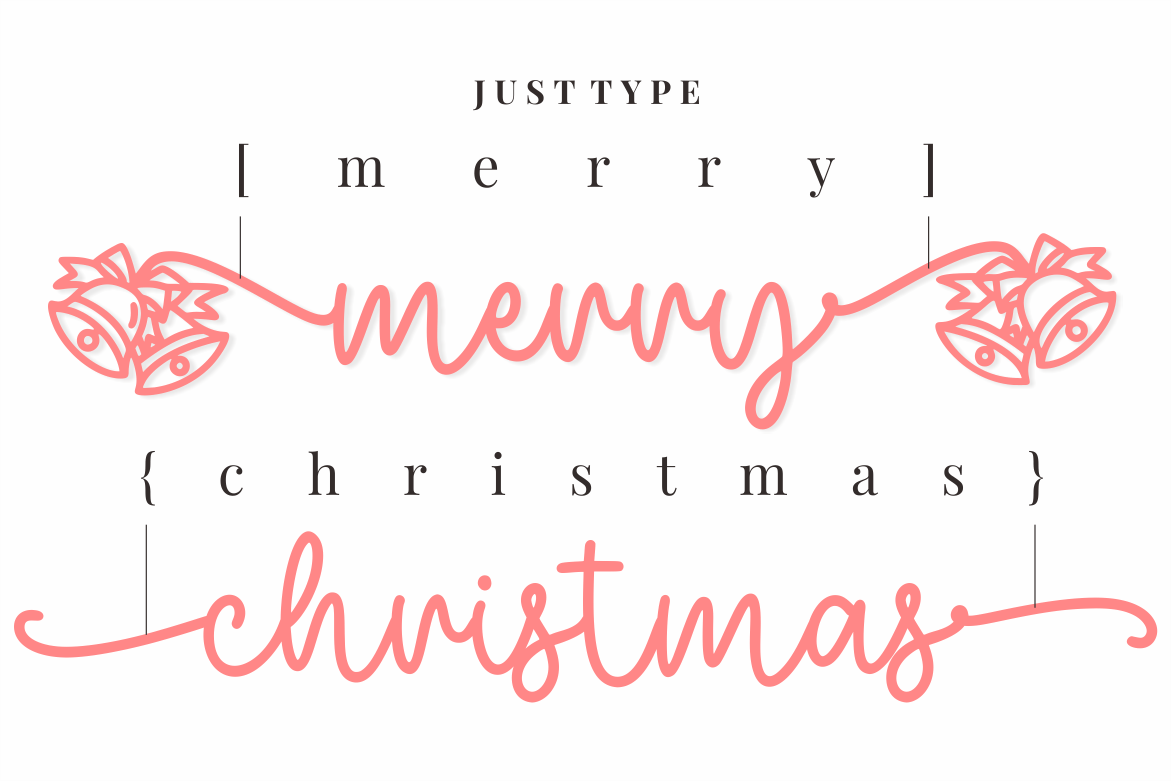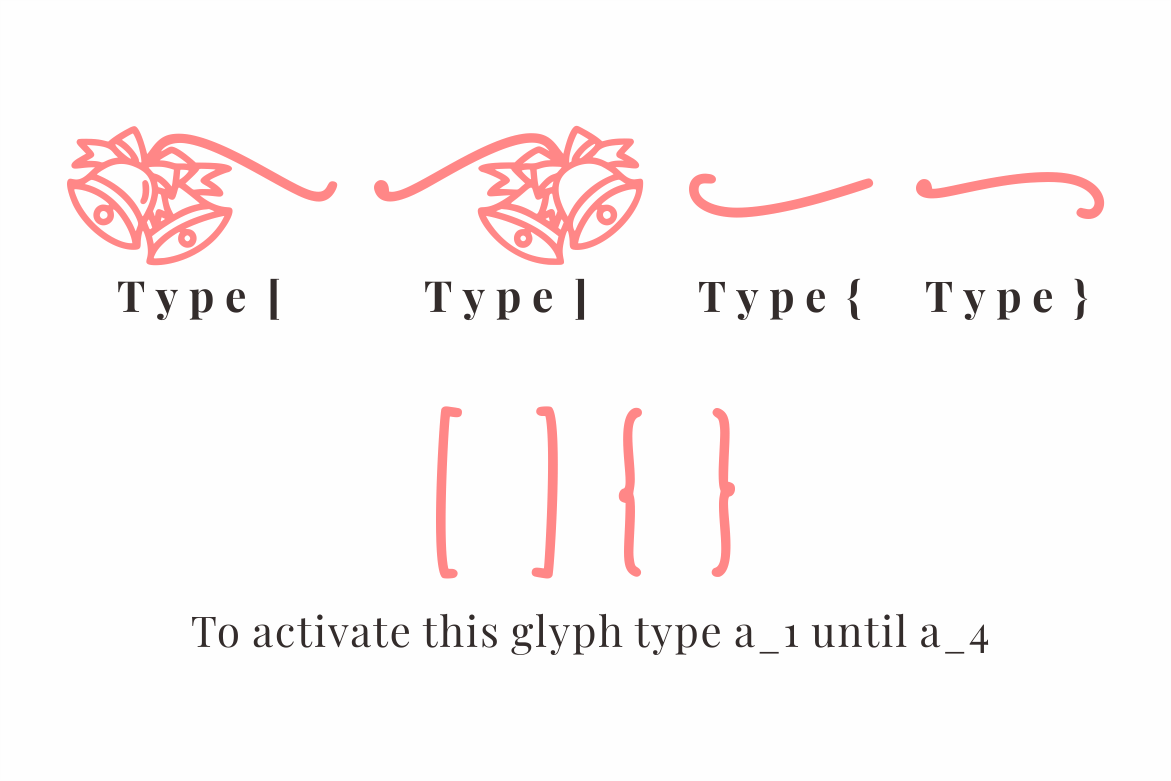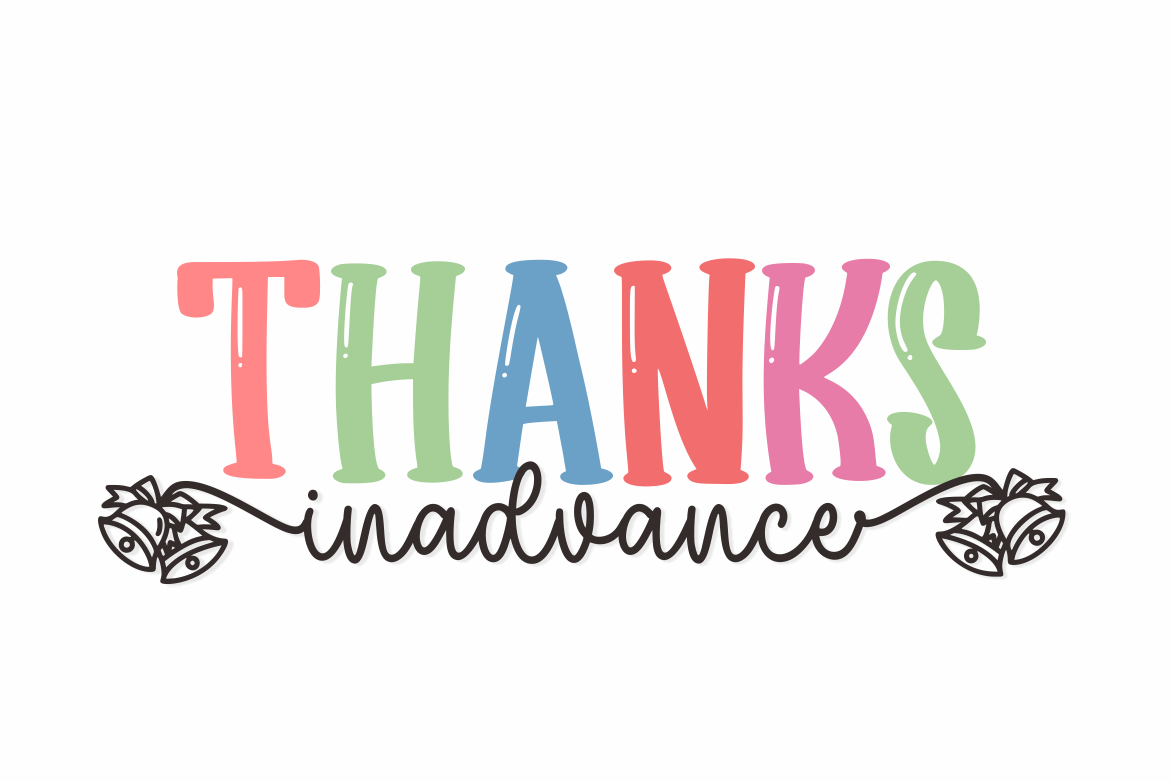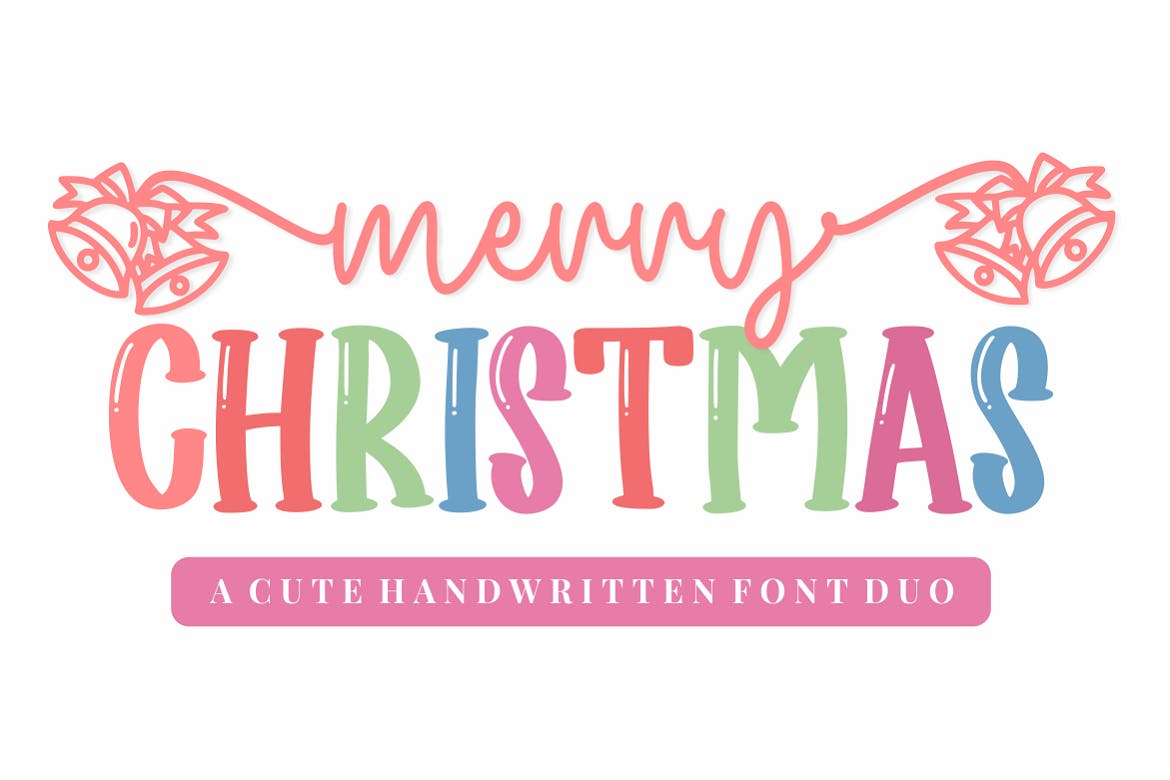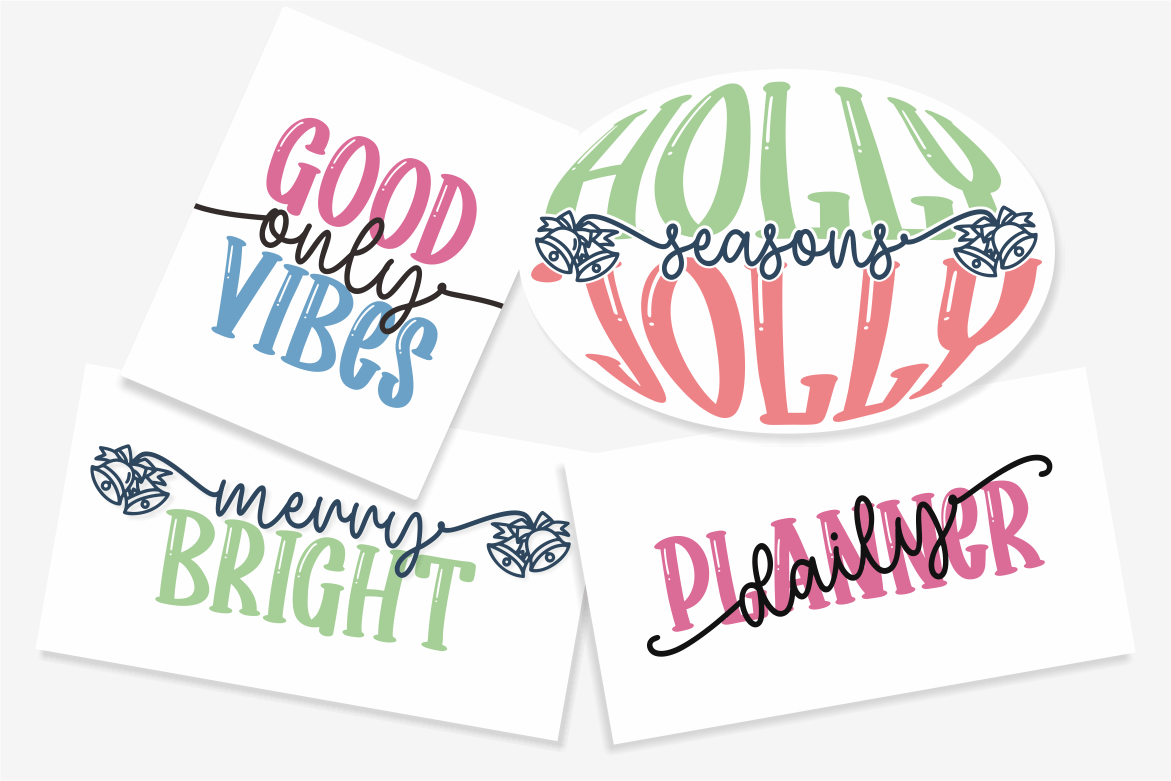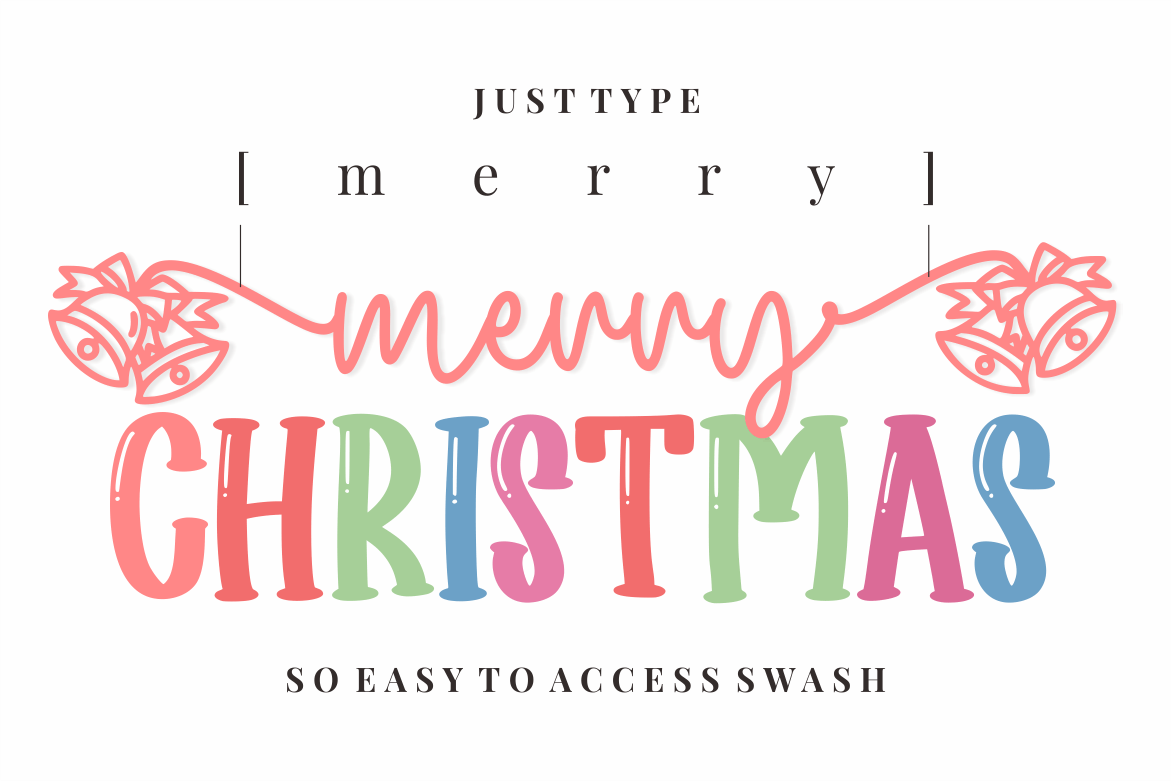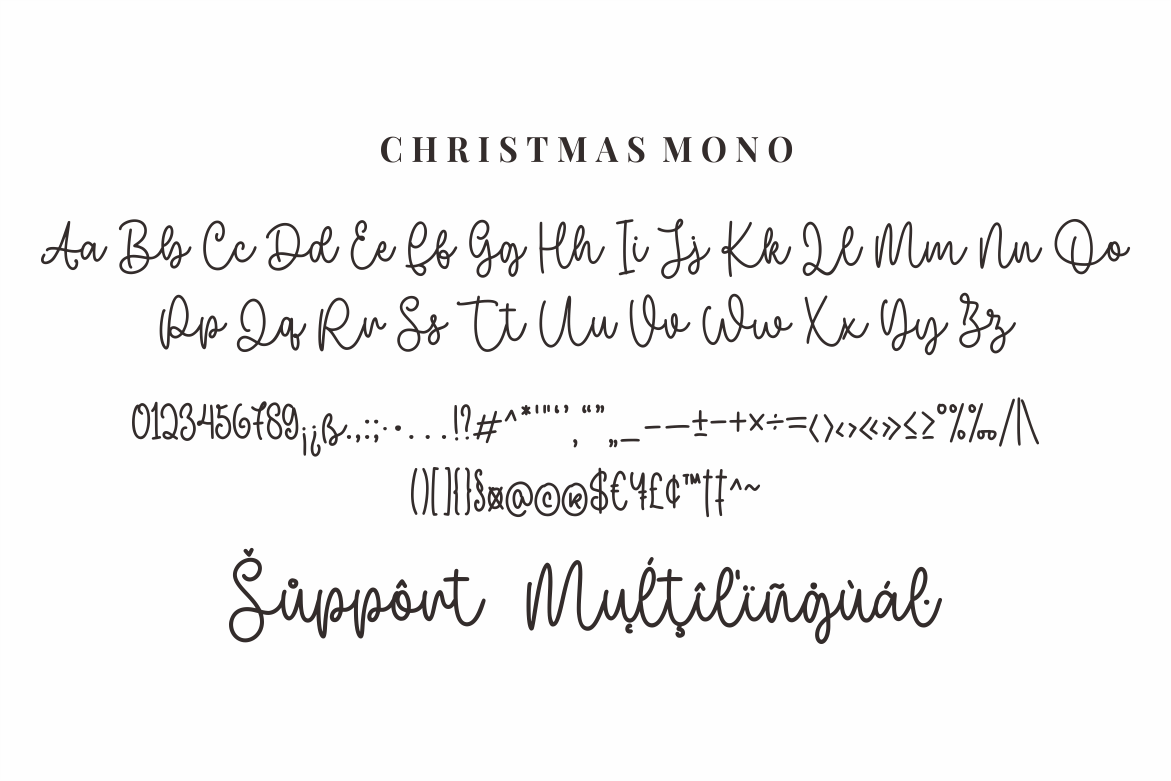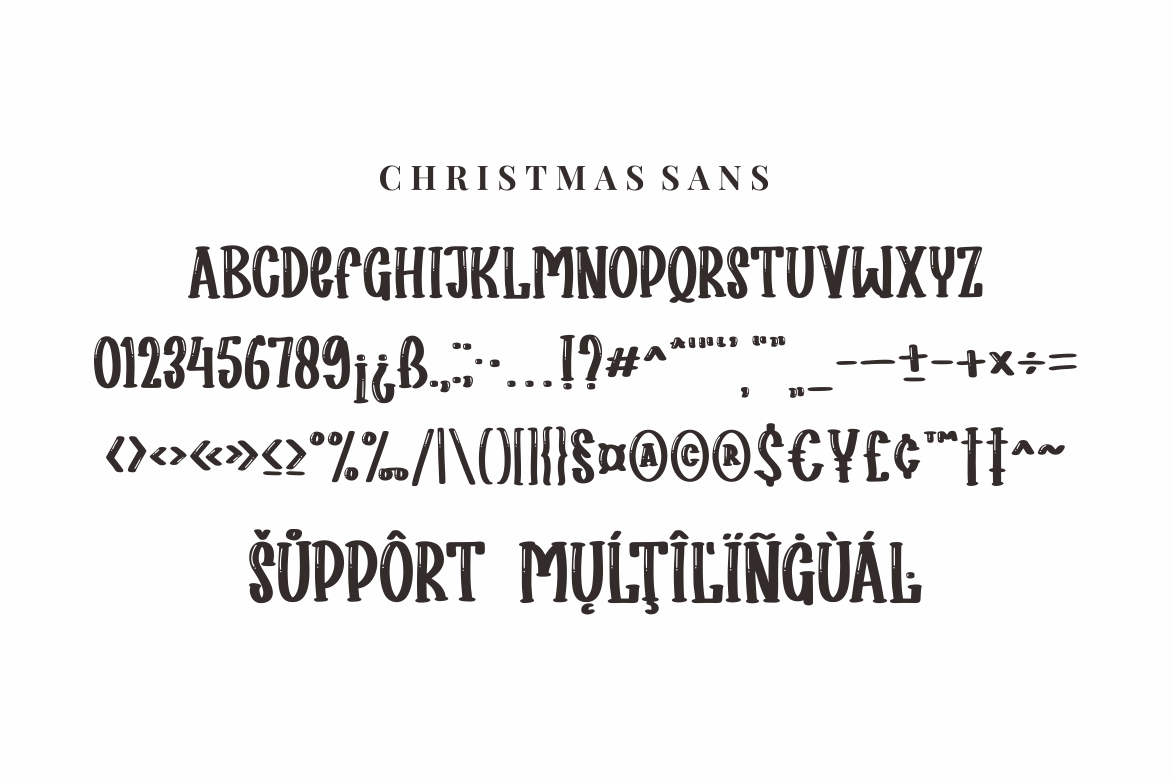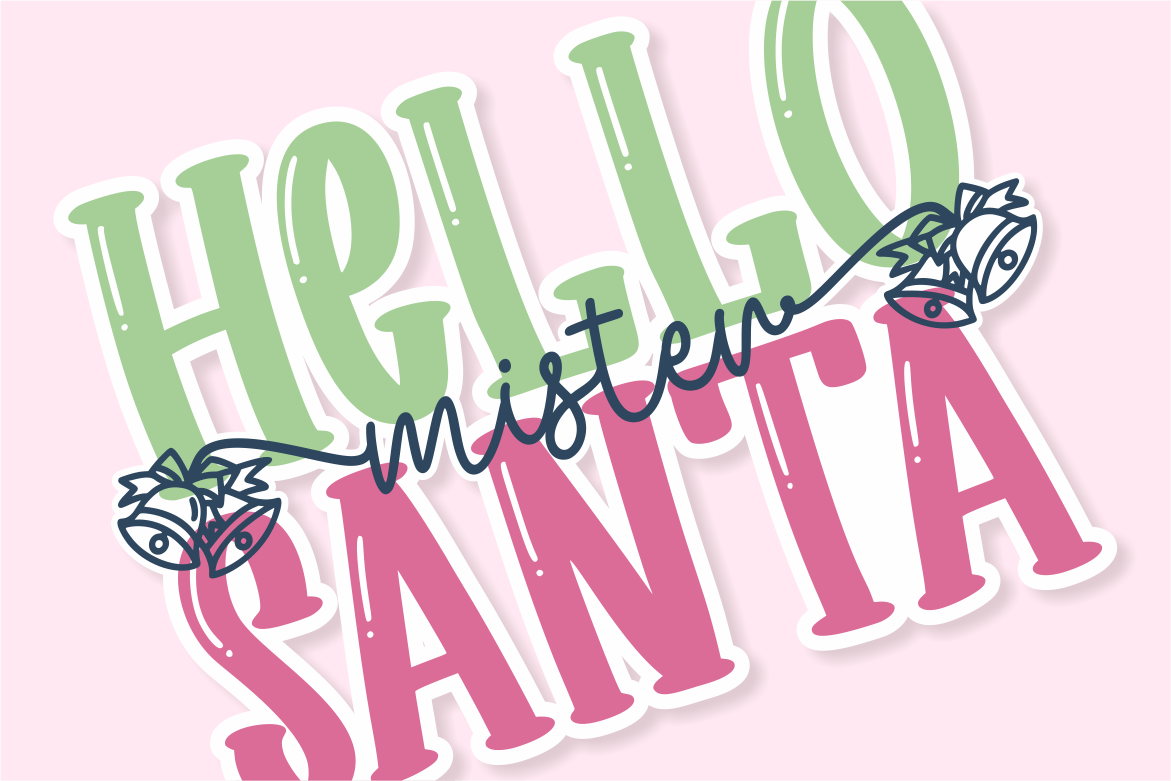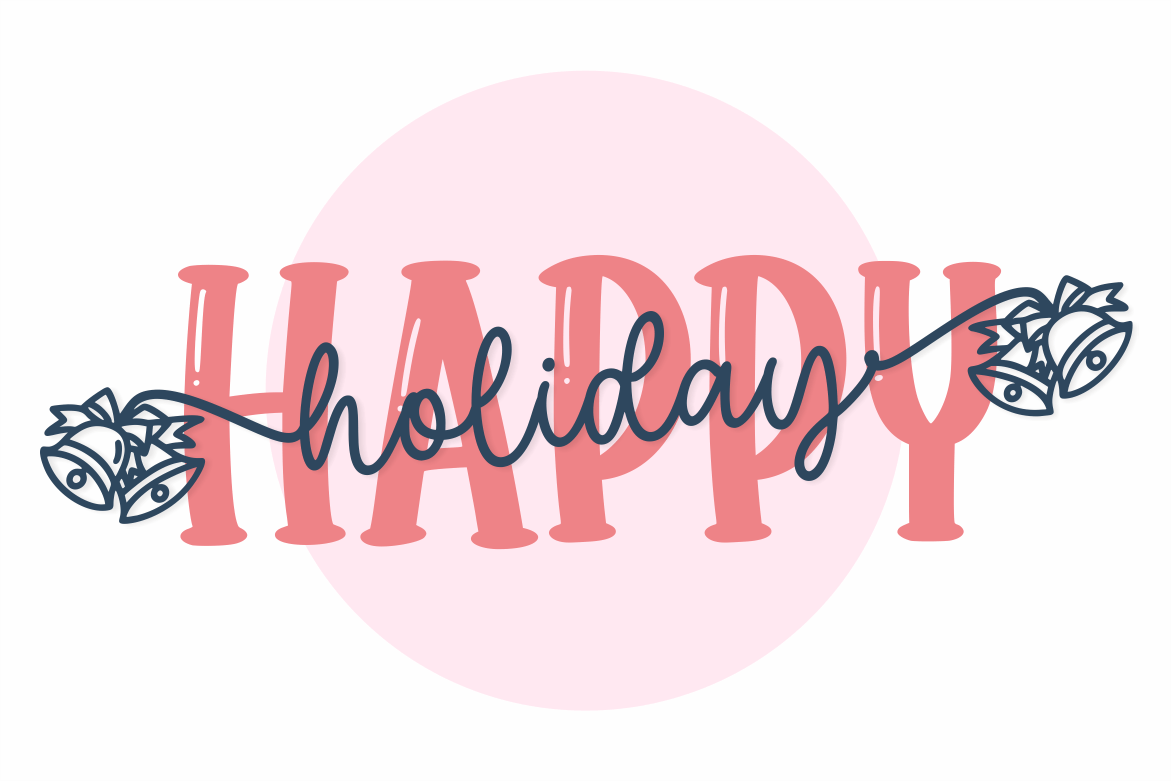
فونت Christmas Duo یک فونت نمایشی جذاب و خاص است که برای نیازهای طراحی شما مناسب میباشد. این فونت برای موضوعات کریسمس، عروسیها، پستهای شبکههای اجتماعی، نقلقولها، روی تصاویر، لوگوهای تبلیغاتی، پوسترها، نیازهای چاپی، بنرهای وبسایت و موارد دیگر کاربرد دارد.